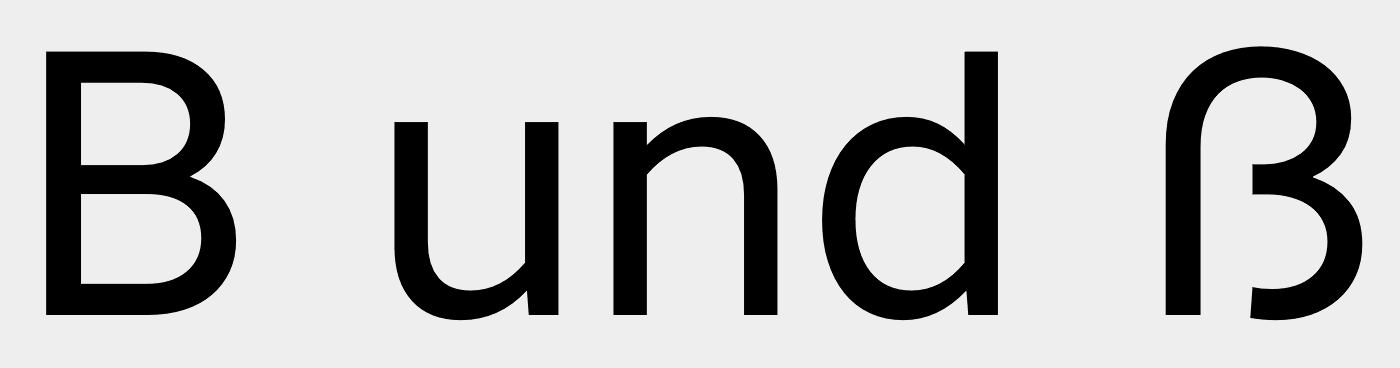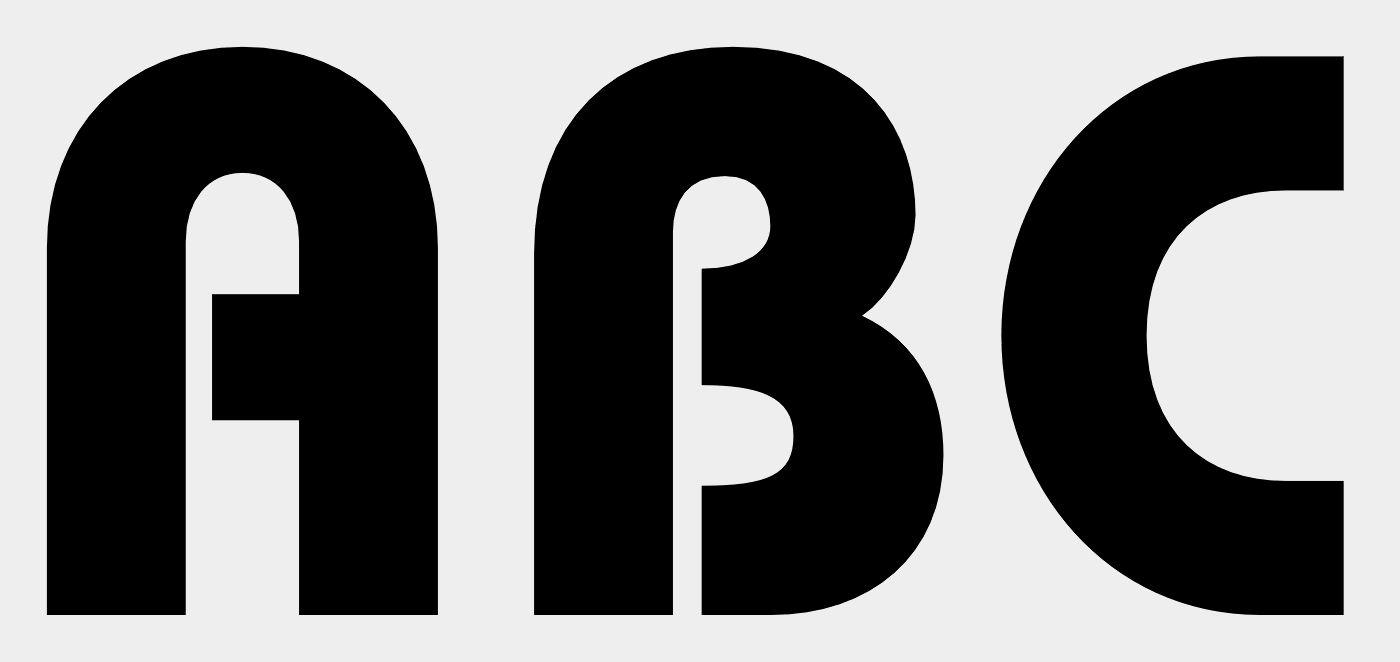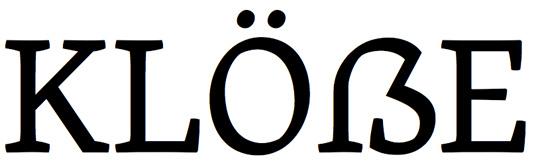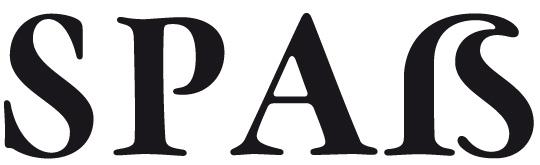
:nicken: Auf den ersten Blick dachte ich das ist die FF Real 2.0 mit einem Schuss Meta drin. :shock:
Trotzdem frage ich mich noch (völlig ergebnisoffen), ob der Weg das ẞ annähernd genauso wie das ß zu gestalten und eben nur die Proportionen an das Versalalphabet anzupassen wirklich so abwegig ist oder nicht doch eine von mehreren Möglichkeiten darstellen könnte … hmmm.
Ich kann für eine deutliche strukturelle Unterscheidung zwischen kleinem und großen Eszett keinen direkten Nutzen oder gar Zwang erkennen. Die Unterscheidung ist kein Selbstzweck. Das Ergebnis muss einfach die gewünschten Anforderungen erfüllen – Versal-Metrik und  -Proportionen, Leserlichkeit/Unterscheidbarkeit. Ein ẞ wie oben fällt aber (für mich) im Punkt Unterscheidbarkeit gnadenlos durch, weil die klare Unterscheidung zum B fehlt. Ein ITC-Bauhaus-B ist halt kein ẞ. Wenn ich es nur über den Kontext unterscheiden muss ist das zu wenig.
Es kann aber durchaus Schriften geben, wo ß und ẞ identisch sind, weil das ß alle genannten Kriterien bereits erfüllt. Ist dann aber sicher eher so etwas wie eine geometrische Blockschrift.
Egal, das Versal-ß der FF DIN wird auch so aussehen. Inwiefern und wie welche Versalien sich von Gemeinen unterscheiden ist eine gestalterische Frage. Ich denke, diese Form des Versal-ß ist ideal für Grotesk-Schriften wie Univers, Helvetica, Unica, DIN, Akzidenz Grotesk und für die meisten klassizistiche Antiqua. Übrigens: Die Grundformen der Versalien C, O, S, V, W, X und Z unterscheiden sich normalerweise auch bocht wesentlich von den der Gemeinen. Ein Buchstabe mehr oder weniger der sich unterscheidet macht den Kohl auch nicht fett.
Und wie ist es mit dem Unterschied zwischen E und F, P und R, O und Q?
Der ist für die allermeisten Leser einfacher auszumachen als der zwischen …
… würde ich mal vermuten. :-?
Nun ja, bei manchen Schriften unterscheiden sich die Zeichen nun mal weniger als bei andere. Man kann ja auch gegen das a der Futura wettern, dass es sich nicht gut genug vom o unterscheidet und da ist ja auch etwas dran. Aber wo wären wir ohne Futura?
Übrigens: Die Grundformen der Versalien C, O, S, V, W, X und Z unterscheiden sich normalerweise auch bocht wesentlich von den der Gemeinen.
Das war auch einer meiner ersten Gedanken nach Ralfs Antwort auf mein Simbilieren. Einen entscheidenden Unterschied gibt es aber dennoch, welcher beim ß fehlt: der Unterschied von Versal- zu x-Höhe.
Egal, das Versal-ß der FF DIN wird auch so aussehen.
Ich denke, diese Form des Versal-ß ist ideal für Grotesk-Schriften wie Univers, Helvetica, Unica, DIN, Akzidenz Grotesk und für die meisten klassizistiche Antiqua.
Weshalb?
Nur damit keine Missverständnisse aufkommen:
Das Problem ist nicht die Stärke der Unterscheidung zwischen B und ẞ innerhalb einer Schrift. Wir lesen Buchstaben einer Schrift nicht vergleichend. Das Problem ist, dass der Leser bei so einer Versaleszett-Form ein B liest oder lesen kann, da alle strukturellen Merkmale eine B erfüllt sind.
Das ist ein B. Die Lücke unten ist irrelevant. Sie gehört wie die beim A nicht zu den strukturellen Merkmalen des Zeichen.
Wenn ein Zeichen sich exakt dieses Bauplans bedient, aber für ein ganz anderes Zeichen stehen soll, dann haben wir bzw. der Leser ein Problem. Daher warne ich ja seit 2011 alle Schriftgestalter ausdrücklich vor diesem Ansatz.
Aber ist dann ein kleines ß (das der San Francisco sieht zum Beispiel genauso aus) auch ein B?
Das ist theoretisch (z.B. bei alleinstehenden Zeichen) auch ein Problem, aber ß und B sind ja etablierte Zeichen. Die müssen wir jetzt nicht auch noch infrage stellen. ;-)
In der (bisherigen) Praxis macht es der Kontext eindeutig – und damit meine ich nicht den Inhalt, den man erst lesen und verstehen muss, sondern die bloße Wortstellung. In Straße (gemischter Satz) kann es kein Großbuchstabe sein. Bei Bauhaus kann es kein Eszett sein, weil es nie am Wortanfang steht. Über GROß als potenziell »grob« wurde sich seit Jahren lustig gemacht. Das verdeutlicht das Problem.
Und bei WEIẞ vs. WEIB würde es sich fortsetzen. Es sei denn, man gibt dem ẞ ein eigenes Skelett, dass nicht als B gelesen wird. Rechts oben eine Diagonale oder ein nach innen gewölbter Bogen (wie beim S) schaffen das erfolgreich. Die Brechung bricht im wahrsten Sinne des Wortes mit der Lesegewohnheit des B.
Das große B der ITC Bauhaus ist m.E. ein individueller Sonderfall, den ich nicht zum entscheidenden Kriterium bei diesem Thema machen würde. Ich finde die Form mit den zwei Rundungen stellt eine Möglichkeit dar, wenn auch viell. nicht die hauptsächlich zu empfehlende.
Diese relativ B-ähnliche Form finde ich jedenfalls längst nicht so falsch wie die ›Leipziger (Duden-)form‹ wie hier gezeigt in SPAẞ.
Schön, dass das Versal-Eszett hier zur Anwendung kam!
Was mir an der Form des Versal-Eszetts auffällt: Mir erscheint es auf den ersten Blick minimal zu klein und zu schmal zu sein. Das kann aber daran liegen, dass die Punzen den Buchstaben recht kleinteilig wirken lassen. Er erscheint weniger klar und aufgeräumt als die Kollegen um ihn herum. Ich hätte an dieser Stelle wohl ein weniger organisch anmutendes Zeichen erwartet, weil die übrige Schriftform doch sehr geometrisch auf mich wirkt. Nur mal so als Rückmeldung.